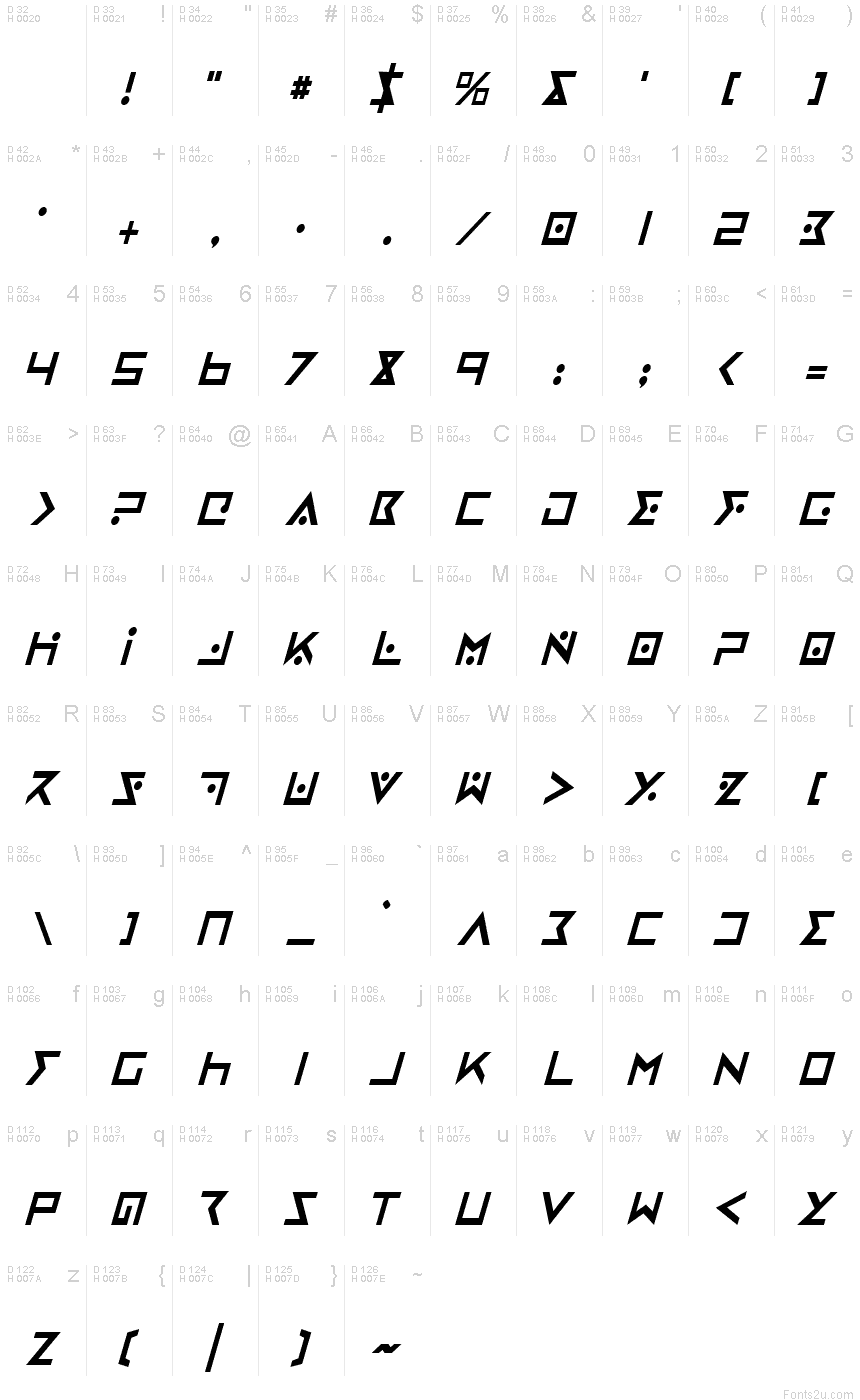
Iron Cobra Condensed Italic od Iconian Fonts to darmowy, techniczny krój pisma typu display, wyróżniający się ostrym pochyleniem i futurystycznym charakterem. Szerokie, geometryczne kreski, ścięte rogi i dramatyczne ukośne cięcia nadają literom wygląd spersonalizowanego emblematu wyścigowego lub futurystycznego oznaczenia maszyny.
Ten darmowy font świetnie sprawdzi się w brandingu e-sportowym, grafikach związanych ze sportami motorowymi, tytułach gier, okładkach albumów oraz plakatach wydarzeń technologicznych. Dobrze sprawdza się również w krótkich nagłówkach i planszach tytułowych, gdzie wydłużone formy i kąty ostre niczym ostrza mają wystarczająco dużo przestrzeni, by wywrzeć odpowiednie wrażenie.
Iron Cobra Condensed Italic
Condensed Italic